Les bests de la fonderie Fontfabric.
Sélectionnés par le Monotype Studio.
Fontfabric.
Fontfabric est une fonderie de caractères reconnue au niveau international, fondée à Sofia, en Bulgarie, par Svet Simov en 2008. Cette équipe compacte de designers talentueux et multidisciplinaires est passionnée par les polices de caractères de haute qualité, la calligraphie et le lettrage, et se concentre sur la création de polices de caractères impeccables et accessibles aux clients.
Mont
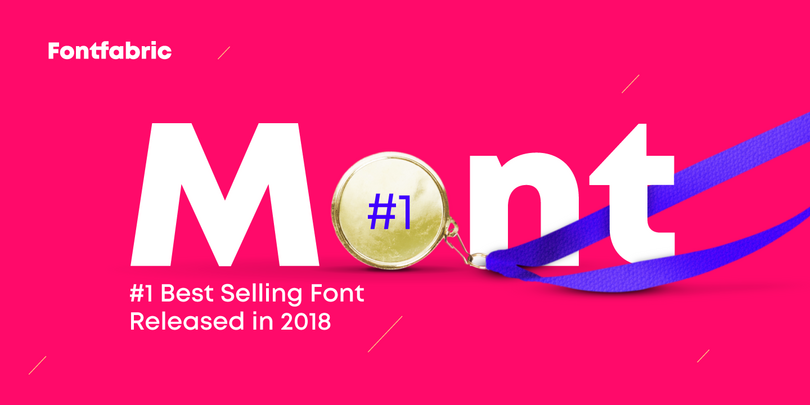
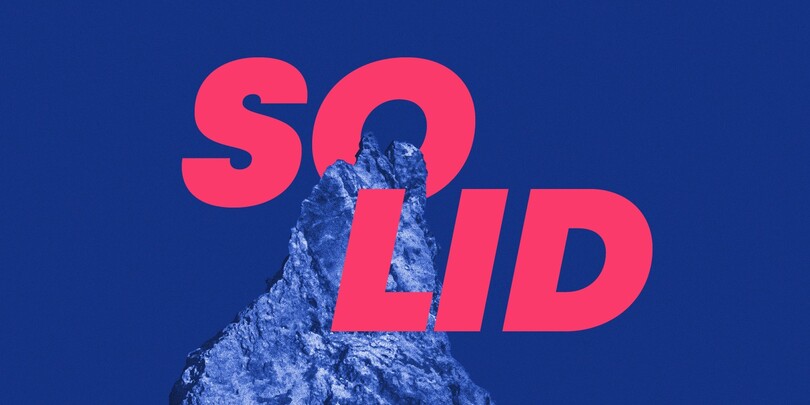
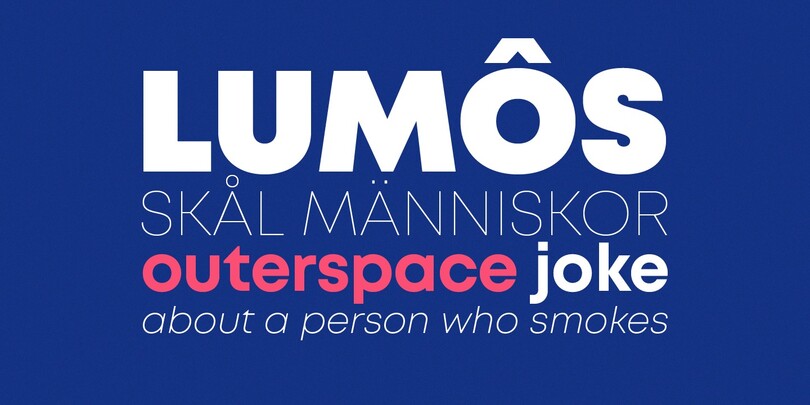
Mont est une police sans empattement géométrique composée de 10 graisses allant de Hairline à Black, avec les italiques correspondants. Elle prend en charge le latin étendu, le cyrillique et le grec, soit plus de 130 langues au total. Les caractéristiques équilibrées de la police Mont, avec des détails uniques tels que le “t” pointu et sa hauteur d’œil proéminente, la rendent parfaite pour les titres forts et les logos exceptionnels, mais aussi pour les textes longs.
Nexa
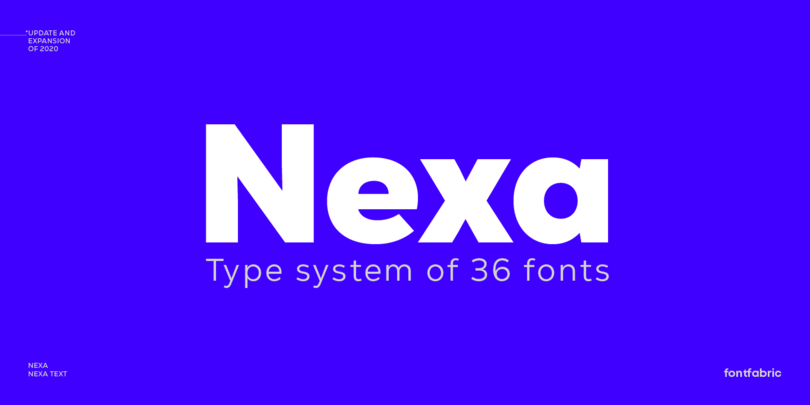
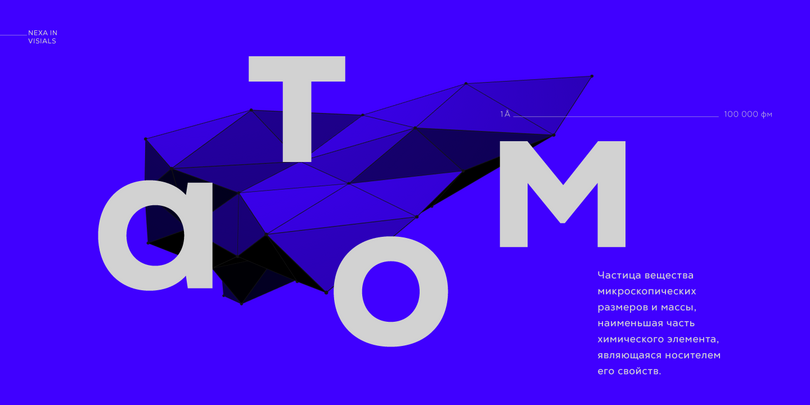
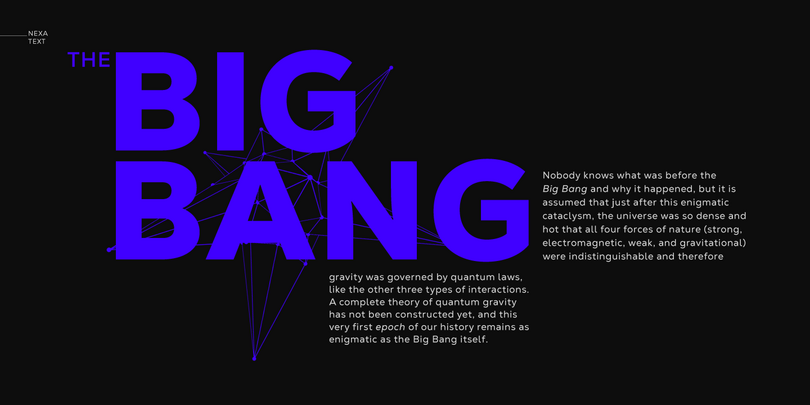
Même les polices de caractères les plus reconnaissables de notre époque devraient être mises à jour parfois, et la Nexa ne fait pas exception. Fontfabric a récemment mis à jour cette fameuse police sans empattement géométrique, en ajoutant une nouvelle sous-famille Text et une graisse Extra Light. L’aspect unique de la Nexa, combiné à sa grande variété de graisses, la place au-delà des polices de caractères géométriques ordinaires et la rende adaptable à toutes sortes d’échelles, d’usages et de conceptions.
Panton
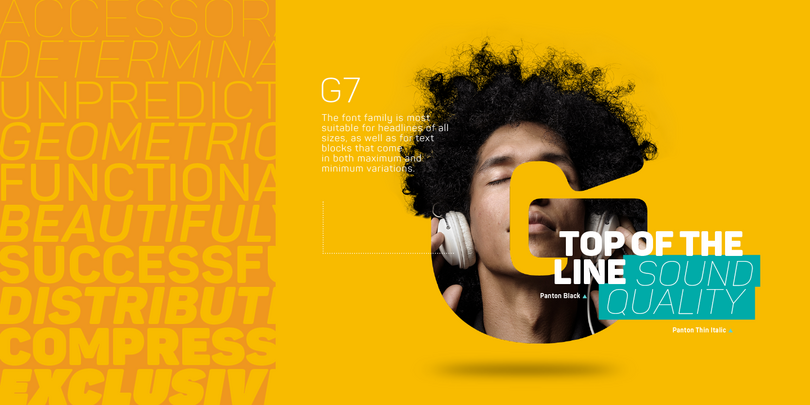
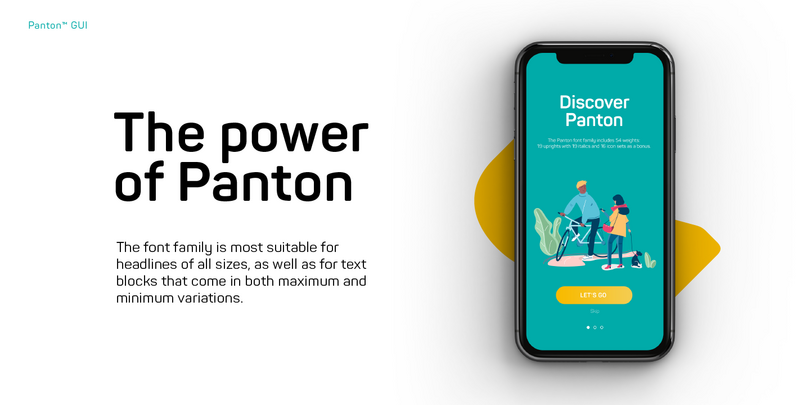
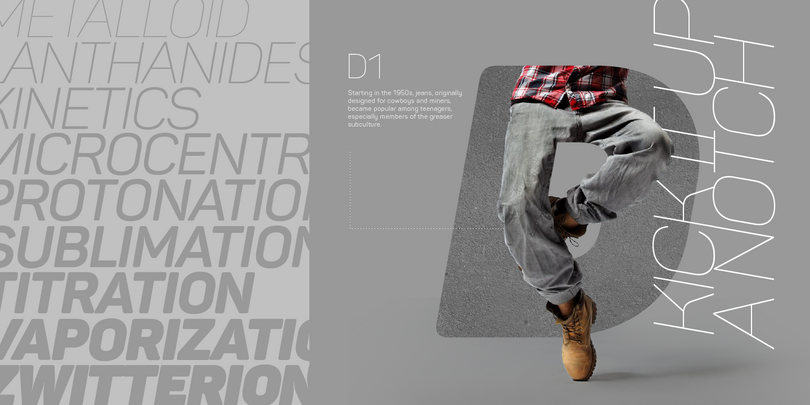
La famille Panton comprend 54 polices composées de 19 graisses normales, 19 italiques correspondantes, et 16 jeux d’icônes en bonus. Elle se caractérise par une excellente lisibilité sur le web et à l’impression, des dessins géométriques bien finis, un crénage optimisé et d’excellentes performances pour ses polices web.
Inspirée par les polices de caractères grotesques classiques, la Panton a son propre style unique, qui s’exprime dans des formes géométriques parfaitement adoucies.
Cette famille de polices convient parfaitement aux titres de toutes tailles, ainsi qu’aux blocs de texte qui présentent des variations maximales et minimales. Les styles de police Panton sont applicables à tout type de conception graphique dans le web, l’impression, les motion graphics, etc. et sont parfaits pour les T-shirts et autres articles comme les affiches et les logos.
Intro
La famille Intro, nouvelle et améliorée, contient 72 polices de caractères et a récemment été élargie pour couvrir d’autres langues. L’aspect ludique raffiné d’Intro est encore accentué par l’ajout de multiples ingrédients, tels que des alternatives obliques soigneusement ajustées à côté des alternatives verticales existantes. Tous ces styles sont désormais disponibles en version condensée. De plus, il y a 3 nouvelles polices de caractères “inline”.
Le nombre de glyphes a été élargi pour couvrir le latin étendu et le cyrillique avec une localisation linguistique adéquate. Les fonctionnalités OpenType ont été réécrites et améliorées pour permettre des formes sensibles à la casse et des variantes contextuelles, ainsi que de nombreuses variantes stylistiques. Le jeu de chiffres standard comprend des chiffres et des symboles tabulaires, des supérieurs et des inférieurs, des numérateurs et des dénominateurs, ainsi que des fractions.
Intro Rust
La gigantesque famille de polices Intro Rust, composée de 214 polices, peut être utilisée pour créer presque tout type de projet dans le domaine de l’impression ou de la conception de sites web. Il suffit d’utiliser votre imagination et votre projet deviendra plus vivant que jamais avec l’une des polices Intro Rust.
Vous voulez réaliser une carte de vœux ou un emballage, ou même une identité de marque ? N’hésitez pas à jouer avec tous les motifs, les formes et les écritures ou ces superbes polices à points et cela vous mènera à votre prochain projet avec succès.
Intro Script
Intro Script capte un sentiment de résurgence, de renouveau et de liberté inconditionnelle. C’est une version actualisée et élargie de la sous-famille Intro Rust, elle-même développée à partir de la famille Intro. Elle est livrée avec 8 graisses différentes et toute une série de bonus et de fonctionnalités supplémentaires à bricoler. Celles-ci consistent en 3 polices supplémentaires avec des mots, des motifs et même des bannières tout prêts, afin que vous puissiez remettre l’étincelle dans votre projet.
L’ensemble comprend un grand nombre de ligatures et de variantes contextuelles, y compris des versions minuscules et majuscules, ainsi que des variations de position. Ces dernières permettent aux symboles de se connecter à différentes articulations et vous aident à éviter les vides inutiles, ce qui se traduit par un processus de travail efficace et un flux plus naturel.
Ces polices incluent une couverture étendue du latin au cyrillique, offrant une prise en charge de plus de 130 langues. Cet ensemble artisanal a été créé pour donner naissance à une typo vintage authentique et original, ce qui la rend particulièrement adaptée à tout design qui suggère un savoir-faire, une sublime touche humaine et une signature mature à la saveur indéniable.